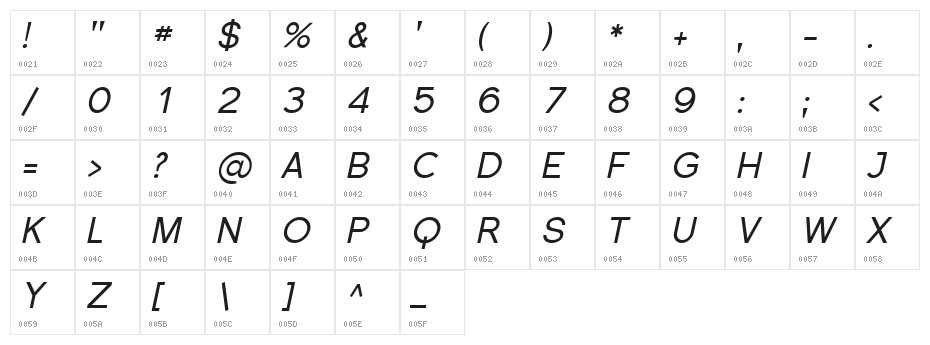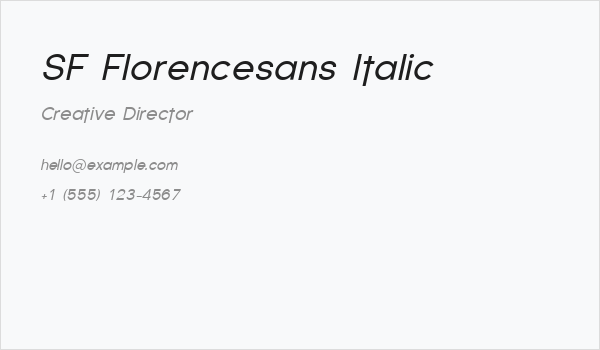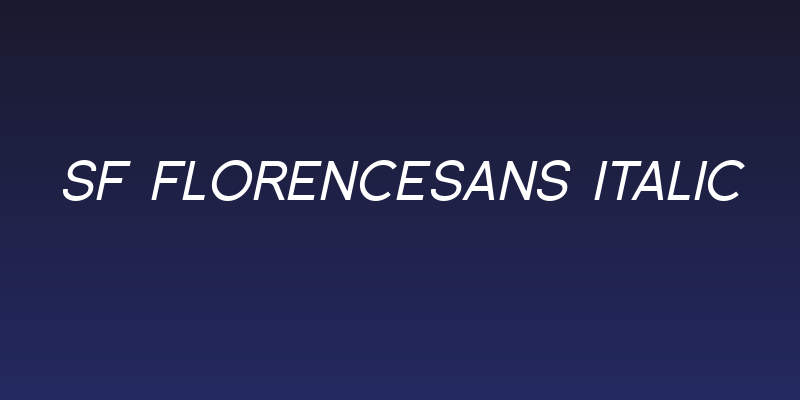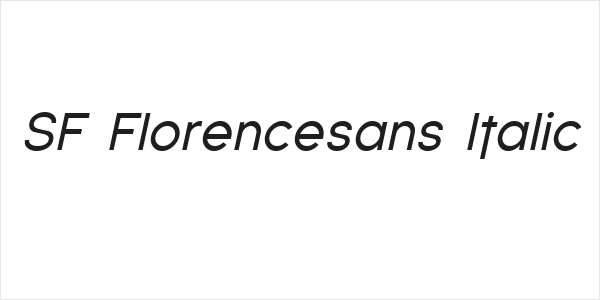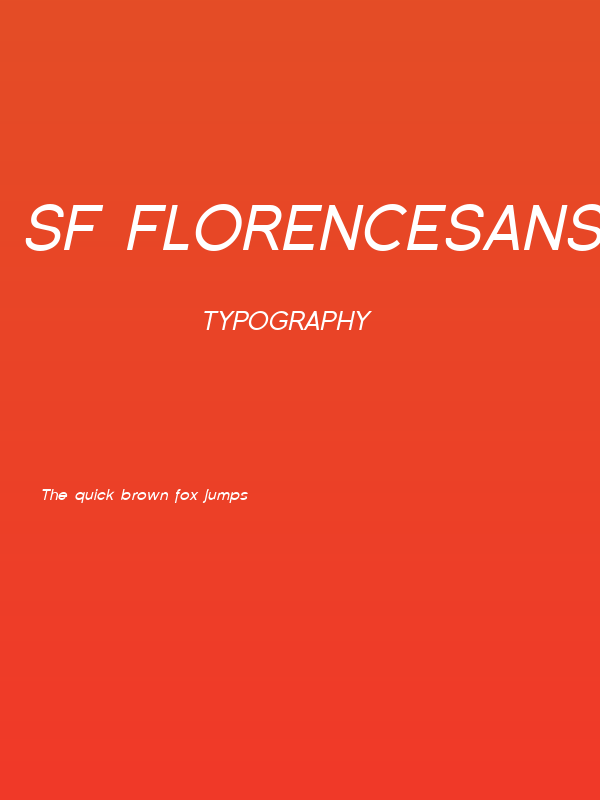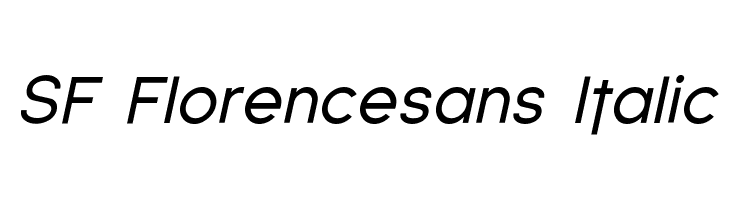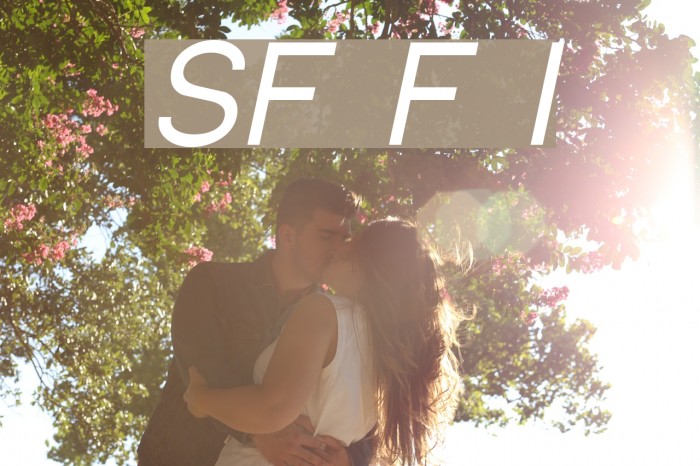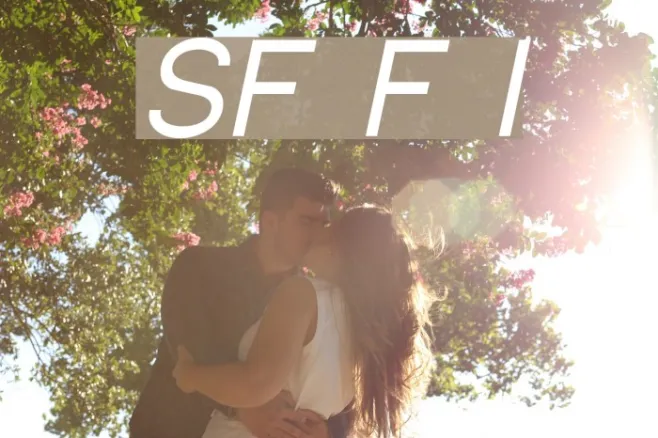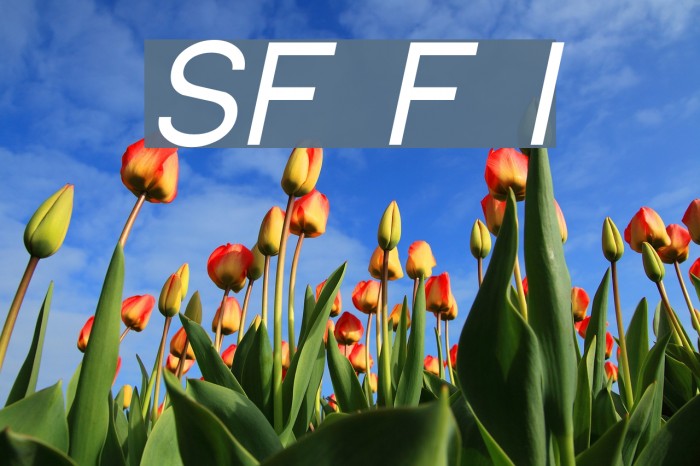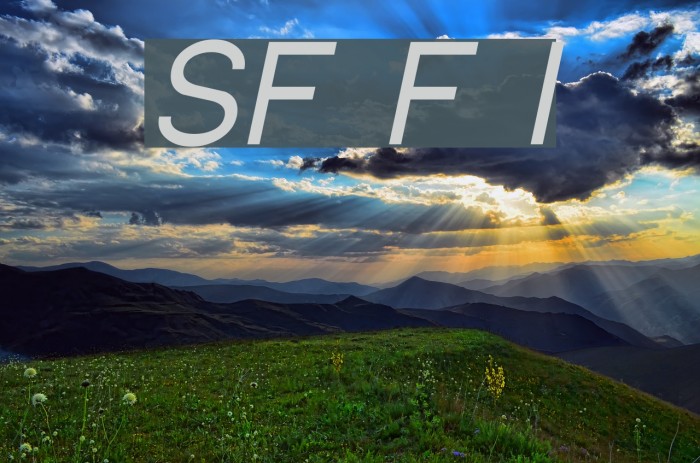
SF Florencesans Italic Font
| Progetti proposti | Ideal for branding, advertising, digital interfaces, and editorial design where a modern and sleek appearance is desired. |